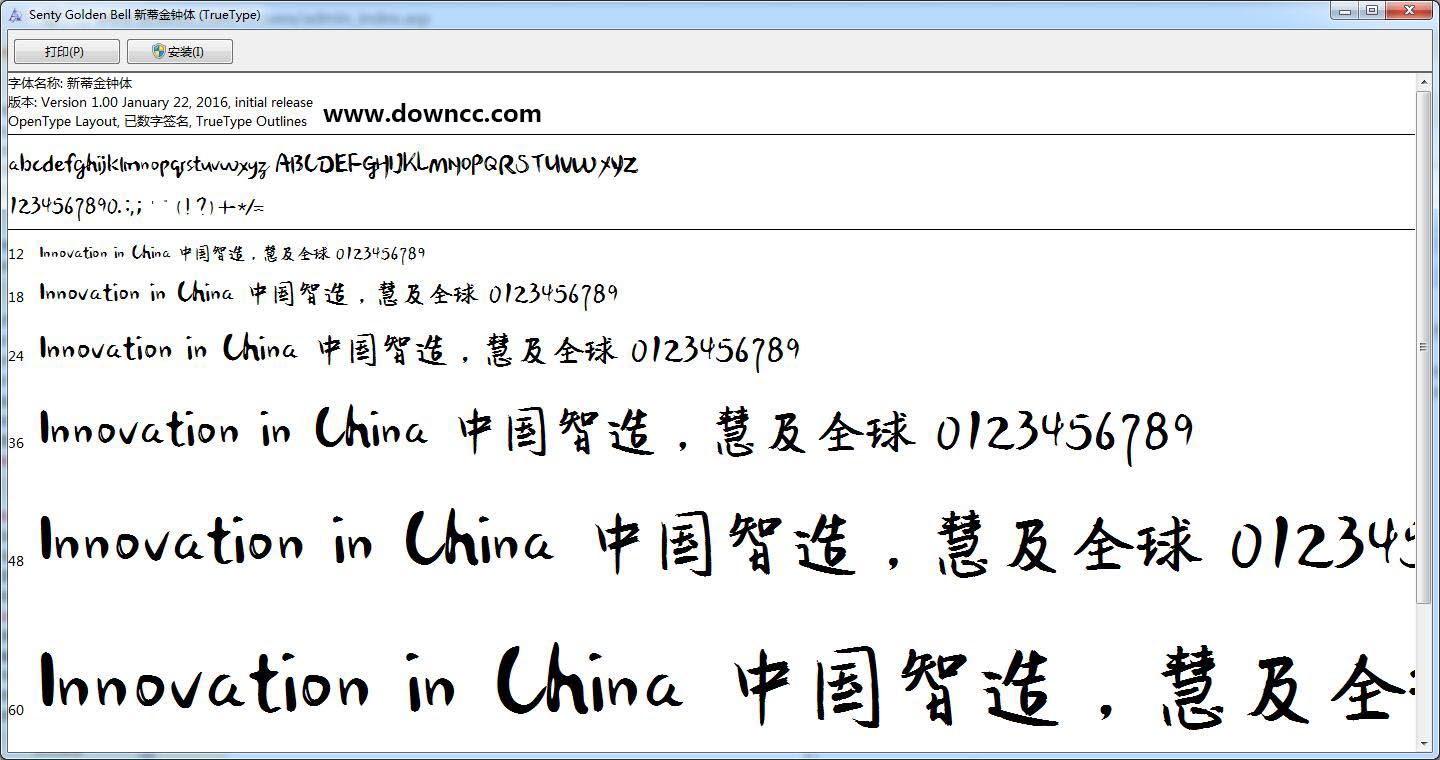
新蒂金鐘體(SentyGoldenBell)是一款應(yīng)用于藝術(shù)設(shè)計(jì)方面的中文簡體漢字,該字體筆畫鋒利,整體效果非常出眾,覆蓋常用簡體、繁體漢字、拉丁字母、數(shù)字等,可以適用于書報(bào)刊標(biāo)題,廣告設(shè)計(jì)、印刷、商標(biāo)注冊(cè)、名稱、包裝等應(yīng)用!